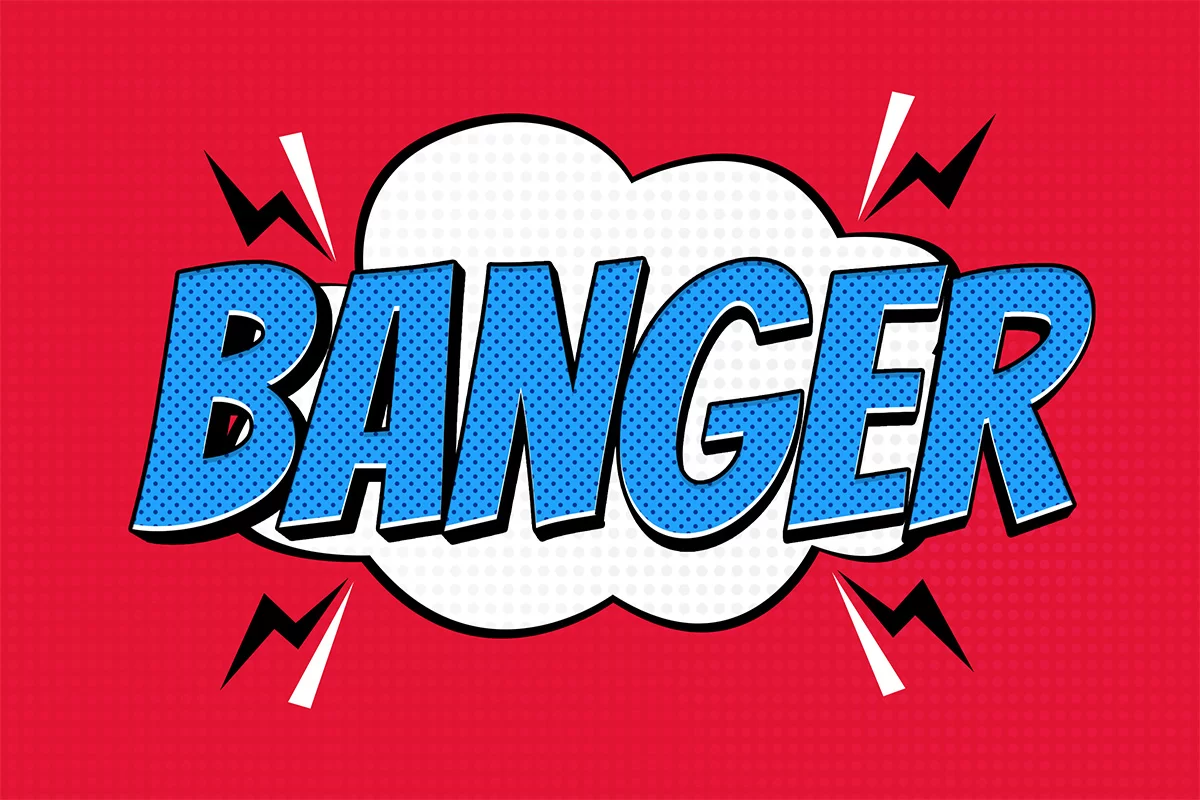
Font Comic Việt hóa là bộ sưu tập các phông chữ mang phong cách truyện tranh (Comic/Cartoon) vui nhộn, sống động và tràn đầy năng lượng tươi mới, được lấy cảm hứng từ những khung thoại và bìa truyện tranh kinh điển. Với những đường nét vẽ tay ngẫu hứng, các góc bo tròn thân thiện và nhịp điệu chữ tự do, nhóm phông chữ này là lựa chọn số một cho các thiết kế bao bì bánh kẹo, đồ chơi trẻ em, đồ ăn vặt và ấn phẩm dành cho giới trẻ. Doozypack.vn cung cấp link tải font Comic Việt hóa chuẩn kỹ thuật, giúp bạn sở hữu kho phông chữ truyện tranh độc đáo mà không lo gặp bất kỳ lỗi hiển thị dấu thanh nào khi thiết kế in ấn.
Đặc điểm thẩm mỹ độc đáo của các dòng font Comic
Font Comic không đi theo sự nghiêm nghị của các phông chữ hình học; nó mở ra một không gian thị giác ngập tràn sự hài hước, dí dỏm và khơi gợi trí tưởng tượng phong phú của người xem.
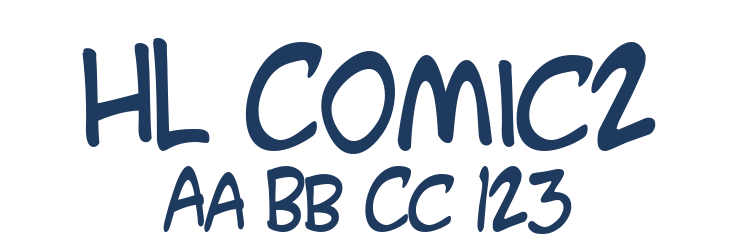
Phong cách truyện tranh vui nhộn và tràn đầy năng lượng
Đặc trưng lớn nhất của font Comic Việt hóa là cấu trúc chữ mô phỏng lại những nét bút lông hoặc bút dạ vẽ tay trong các cuốn truyện tranh thiếu nhi. Nét chữ có độ dày dặn vừa phải, các đường nét hơi xiêu vẹo tự nhiên tạo nên một nhịp điệu Typography vô cùng sinh động. Khi đặt phông chữ này làm tiêu đề trên bao bì, thương hiệu của bạn sẽ ngay lập tức lan tỏa cảm xúc vui vẻ, giúp sản phẩm trở nên nổi bật và kích thích sự tò mò của các bạn nhỏ cũng như các bạn trẻ năng động.
Đường nét vẽ tay ngẫu hứng tạo cảm giác gần gũi
Tất cả các điểm kết thúc và góc nối của dòng font chữ này đều được xử lý mềm mại, loại bỏ hoàn toàn cảm giác sắc nhọn hay khô cứng công nghiệp. Cấu trúc chữ thoáng đãng mang lại tâm lý thoải mái, dễ chịu và cực kỳ thân mật, rất phù hợp với các dòng sản phẩm đồ ăn nhanh, nước giải khát mùa hè hoặc các đồ dùng học tập sáng tạo.
Ưu điểm nổi bật của bản font Comic hỗ trợ tiếng Việt
Khi ứng dụng các phông chữ truyện tranh vào thị trường trong nước, sự chỉn chu về dấu câu là yếu tố quyết định đến tính thẩm mỹ của ấn phẩm:
- Khắc phục triệt để lỗi dấu tiếng Việt: Phiên bản font Comic hỗ trợ tiếng Việt đã được đội ngũ thiết kế trau chuốt thủ công từng dấu câu. Các dấu sắc, huyền, hỏi, ngã, nặng được vẽ với phong cách ngộ nghĩnh đồng điệu cùng thân chữ gốc, không gây cảm giác chắp vá hay đè nét làm biến dạng cấu trúc chữ.
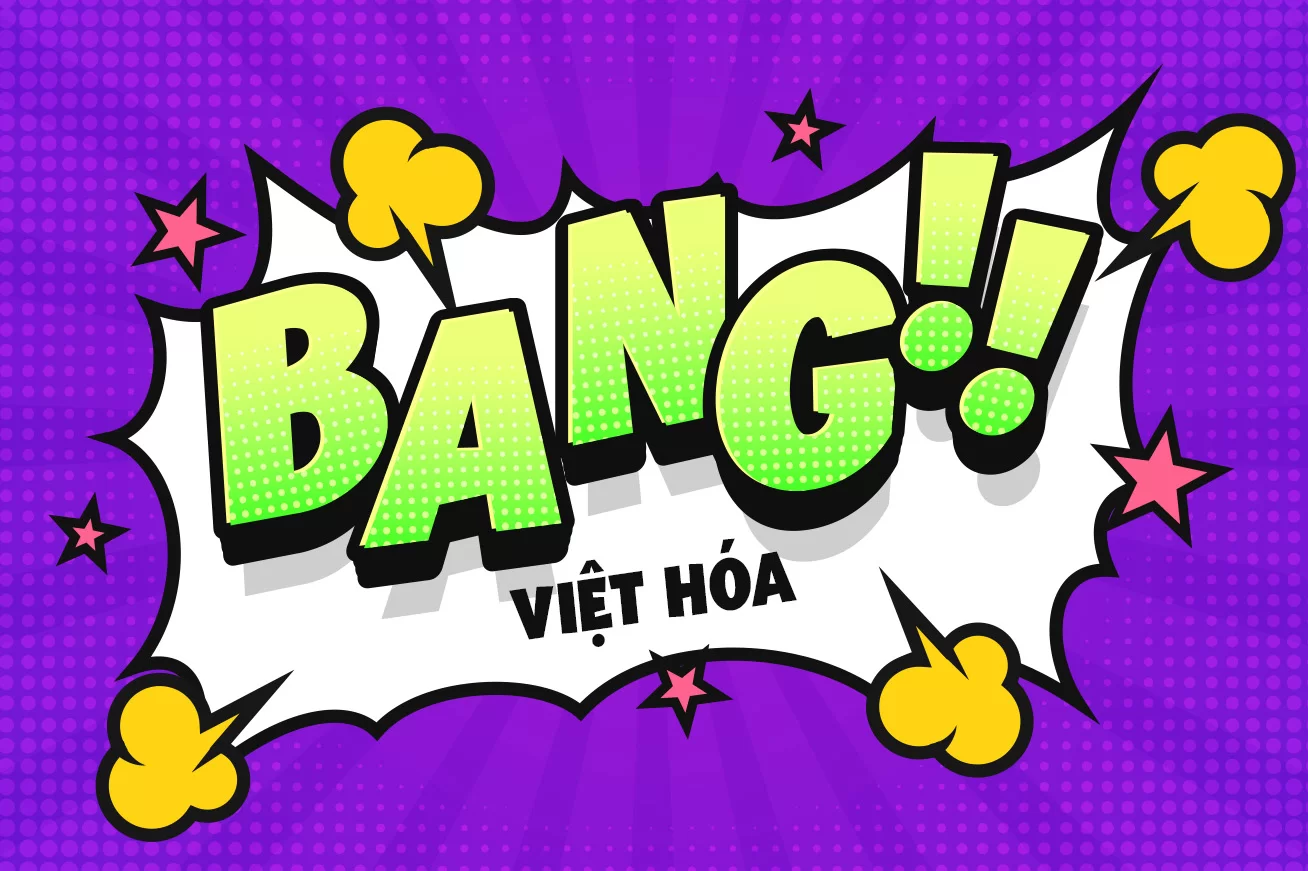
| Nhóm Font | Đặc điểm thị giác | Ứng dụng đề xuất tại Doozypack.vn |
| Comic Bold (Tiêu đề truyện) | Dày dặn, vững chãi, nổi bật | Làm tiêu đề chính hộp quà, bao bì đồ ăn vặt, snack. |
| Comic Dialogue (Hội thoại) | Nét đều, dễ đọc, tự nhiên | Dùng cho các đoạn thoại ngắn, ghi chú trên tem nhãn. |
| Comic Sound Effects (Hiệu ứng) | Nghiêng nhẹ, phá cách, bùng nổ | Thiết kế sticker, poster sự kiện, nhãn dán đồ uống. |
03 Ứng dụng thực tế của font Comic trong sản xuất bao bì tại Doozypack.vn
Sự tươi vui và ngộ nghĩnh của font Comic mang lại hiệu ứng thị giác đắt giá trên các dòng sản phẩm bao bì thực tế do Doozypack.vn sản xuất:
- Bao bì Kẹo ngọt & Đồ ăn vặt (Snacks): Nét chữ hoạt hình gợi cảm giác thơm ngon, rất hợp làm tiêu đề chính trên hộp bánh cookie, túi kẹo dẻo hoặc hộp bỏng ngô rạp chiếu phim.
- Hộp giấy đồ chơi & Sản phẩm thiếu nhi: Tiêu đề in bằng font Comic trên nền hộp giấy rực rỡ tạo sự hào hứng và thu hút sự chú ý của các bạn nhỏ ngay tức thì.
- Tem nhãn dán Sticker & Decal ly nước: Cấu trúc chữ phá cách rất thích hợp để in các tem decal dán ly trà sữa, tem niêm phong hộp hàng, giúp sản phẩm trông sinh động hơn.
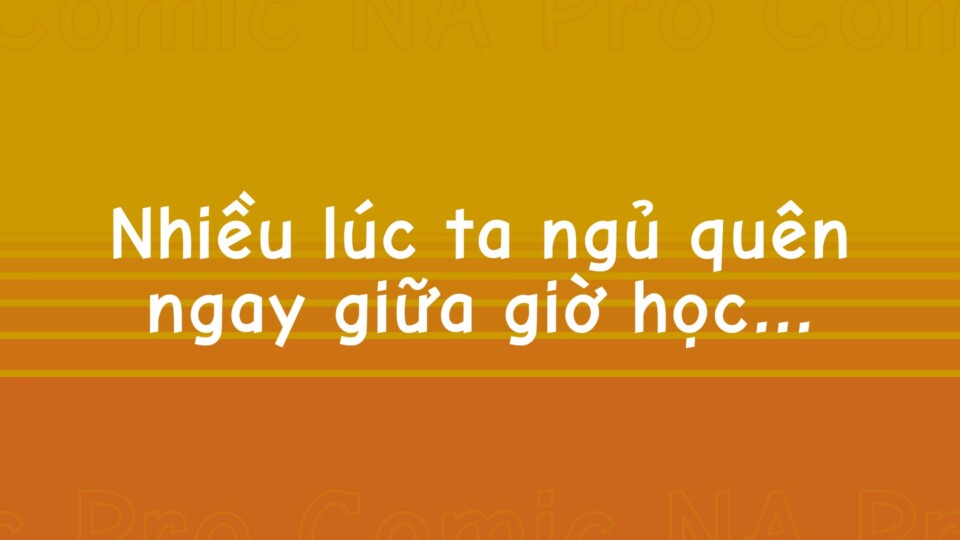
03 Lưu ý kỹ thuật khi in ấn với phông chữ truyện tranh nét dày Comic
Việc sản xuất bao bì thực tế sử dụng các phông chữ có đường nét to bản như Comic đòi hỏi sự am hiểu kỹ thuật chuyên sâu tại xưởng in Doozypack.vn:
- Kiểm soát hiện tượng tràn mực (Dot Gain) tại khe chữ nhỏ: Các khoảng hở bên trong chữ cái khá hẹp ở các biến thể đậm. Khi in trên giấy có độ thấm mực cao như giấy Kraft, mực có thể bị lan làm bít kín các lỗ hở này. Bạn nên giữ size chữ tiêu đề tối thiểu từ 10pt trở lên để bảo đảm độ sắc nét.
- Lựa chọn hệ màu sắc tươi sáng: Phong cách Comic đẹp nhất khi phối cùng các tông màu rực rỡ (vàng chanh, đỏ tươi, xanh dương). Bạn có thể thêm một đường viền (Stroke) mỏng màu đen quanh chữ để tiêu đề nổi bật rõ ràng trên các nền hình ảnh phức tạp.